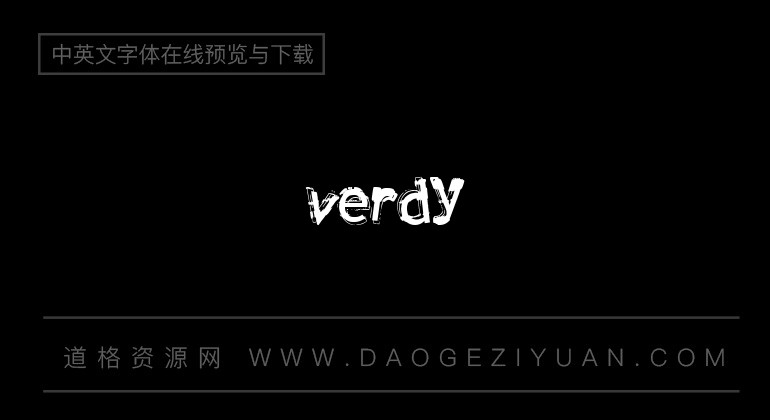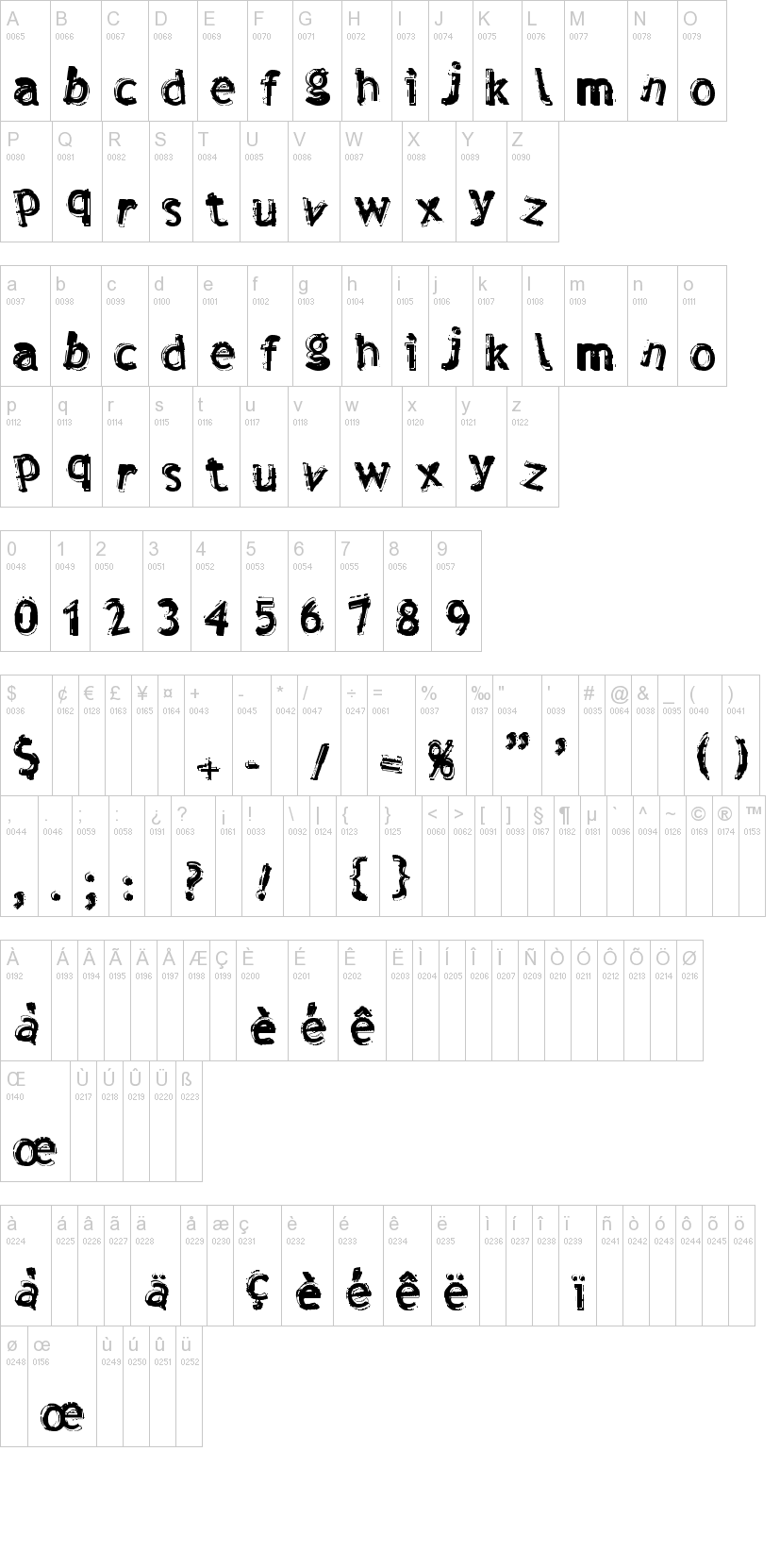
Verdy 字体是一款由日本设计师Verdy Kashiwagi设计的字体,他曾参与过多个全球著名品牌的字体设计,比如:Google、Apple、Adidas、Nike 等。Verdy 字体的特点是拥有类似于欧洲字体的细节和比例,但又有着日本传统的线条和节奏感。Verdy 字体的字符比例紧凑,可以更好地适应屏幕,同时也更加美观。此外,Verdy 字体也具有较强的多语言支持,能够支持多种语言,比如:英语、日语、韩语、汉语等。内容介绍
Verdy是一款非常不错的手写艺术字体,具有很好的视觉感,适合于文化类的宣传设计、商业类品牌的广告和产品包装设计以及个性化文字排版等较多场景。